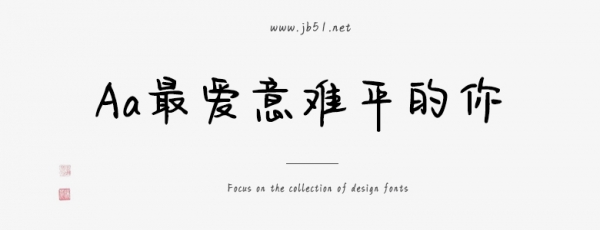
Aa最愛意難平的你是一款不錯(cuò)的藝術(shù)字體,由Aa字庫出品,字體筆觸略細(xì),書寫流暢,具有很好的視覺感,適合應(yīng)用于藝術(shù)設(shè)計(jì)、平面宣傳設(shè)計(jì)、網(wǎng)頁設(shè)計(jì),書法字帖等領(lǐng)域,需要的朋友可以前來本站下載。